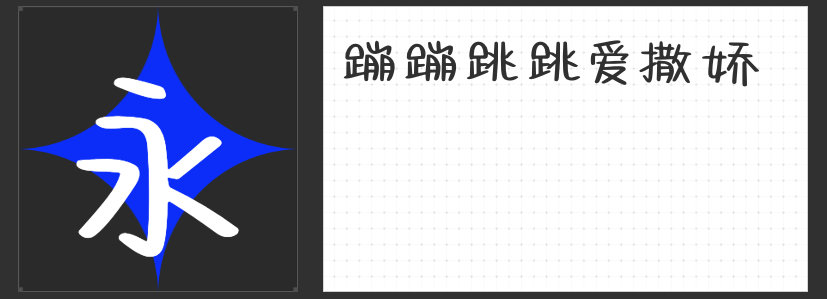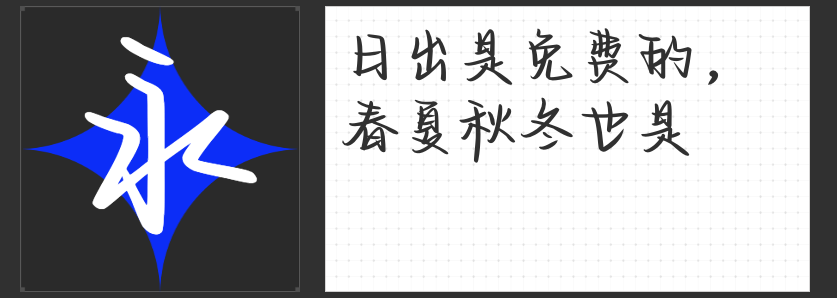
Plog字体新宠儿:四款精选,让你的日常记录更出彩
在数字时代,Plog(照片日志)已成为记录生活点滴、分享个人风格的热门方式。选择合适的字体,能为你的Plog增添无限魅力与个性。今天,就让我们一起探索四款适用于Plog中的字体,让每一次记录都独具特色。
1.高手庆科帅黑体
当聚会的光影与时尚的穿搭成为你Plog的焦点,高手庆科帅黑体以其硬朗倾斜的直线黑体形态,完美诠释出都市生活的干练与不羁。它的每一个字都透露出力量感,适合用来标注聚会主题、强调穿搭亮点,让你的每一张图片都散发着不容忽视的时尚气息。
2.励字圆梦简 常规
对于日常琐碎中的小确幸,励字圆梦简 常规以其圆润柔和的笔触,为Plog增添一抹温馨与俏皮。其直线笔画中融入的自然圆弧,如同生活中的每一个微笑,让人感受到满满的亲和力与幸福感。无论是记录美食探索还是日常趣事,这款字体都能让你的故事更加生动有趣。
3.高手兵克稚趣体
宠物的憨态可掬或是可爱小物的精致瞬间,怎能少得了高手兵克稚趣体的陪伴?这款字体字形结构舒展,笔画设计简单而亲和,洋溢着轻松趣味与随性自然的气息。用它来标注宠物日常或记录那些让人忍俊不禁的可爱瞬间,定能让你的Plog充满童趣与温馨。
想要为你的Plog增添一抹青春与文艺的气息?也字工厂电影旁白体以其独特的手写风格,带你穿越回那个青涩的年华。这款字体洋溢着青春的活力与清新,特别适合用来记录旅行中的清新风景或是那些让人心动的瞬间。它如同电影中的旁白,轻轻诉说着你的故事,让每一次翻阅都成为一次心灵的旅行。
选择适合的字体,就如同为Plog穿上了个性的外衣。无论是硬朗时尚、温馨俏皮、童趣满满还是青春文艺,这四款字体都能让你的Plog更加出彩,记录下每一个值得铭记的瞬间。